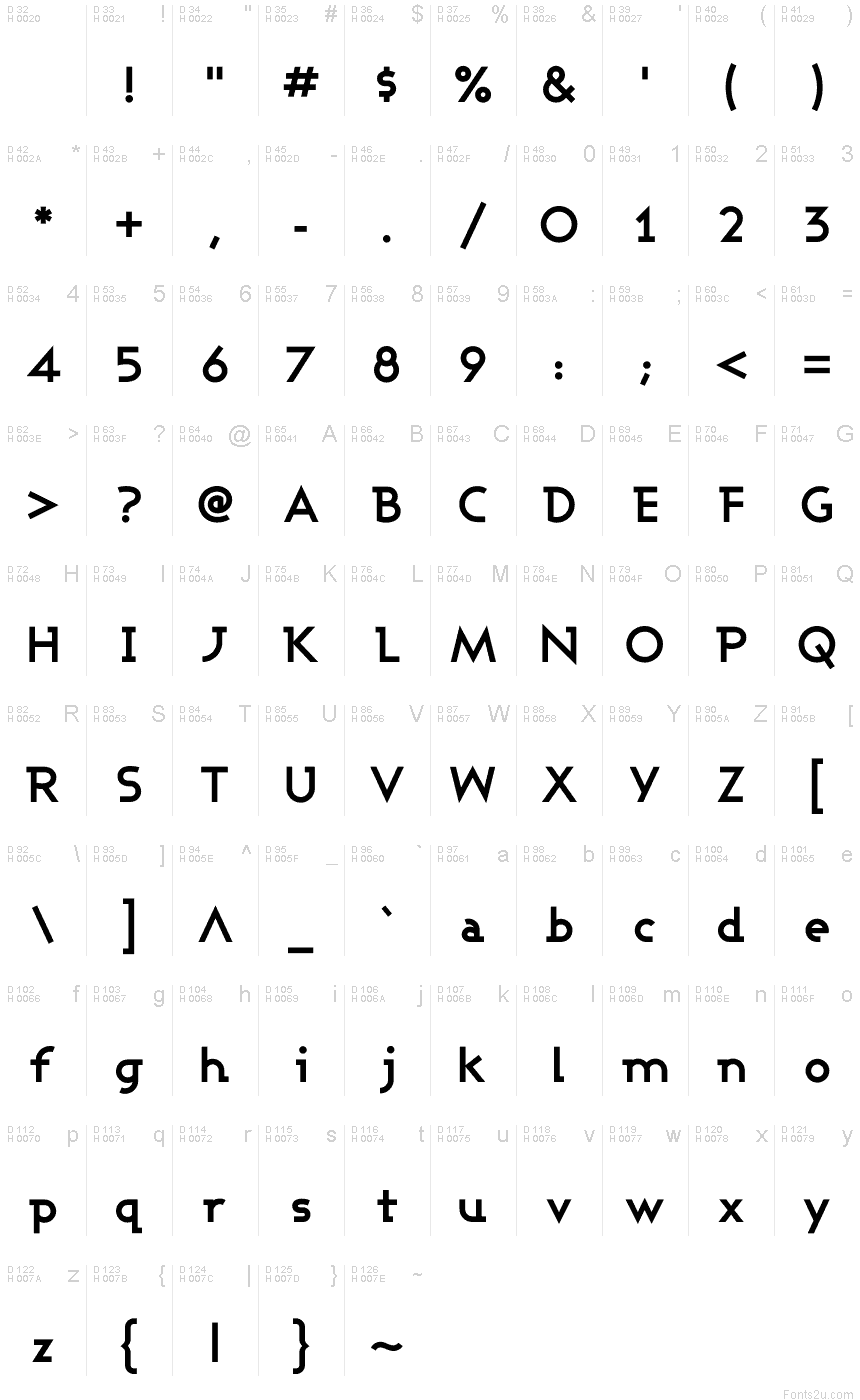
Ashby Bold
Ashby Bold od Robby'ego Woodarda to wyrazisty, geometryczny krój bezszeryfowy, który robi wrażenie, nie będąc przy tym surowym. Szerokie, proste kreski i czyste krzywe nadają mu pewny, zdecydowany charakter, dzięki czemu ten darmowy font idealnie sprawdza się w mocnych logotypach, przyciągających wzrok nagłówkach, plakatach i opakowaniach produktów.
Dzięki prostym formom i równym odstępom, Ashby Bold świetnie sprawdza się również na okładkach magazynów, w systemach oznakowania, identyfikacji wizualnej oraz grafikach do mediów społecznościowych, gdzie kluczowa jest przejrzystość. Ten darmowy font doskonale łączy się z lżejszym, neutralnym krojem bezszeryfowym w mniejszych rozmiarach – niech Ashby przyciąga uwagę w krótkich tekstach, a krój uzupełniający zadba o komfort czytania dłuższych treści.